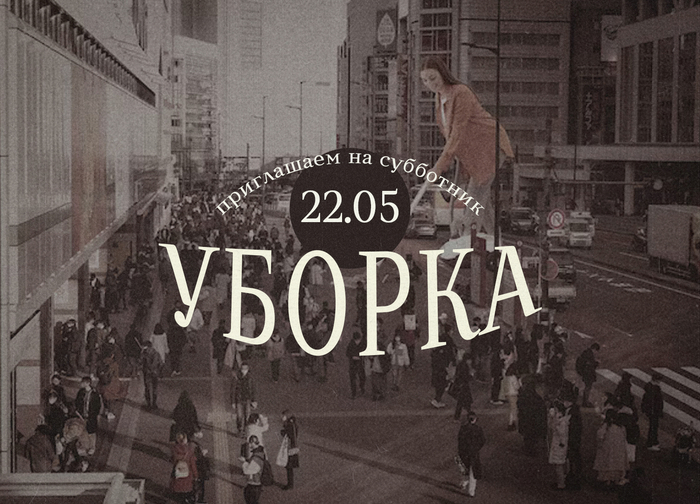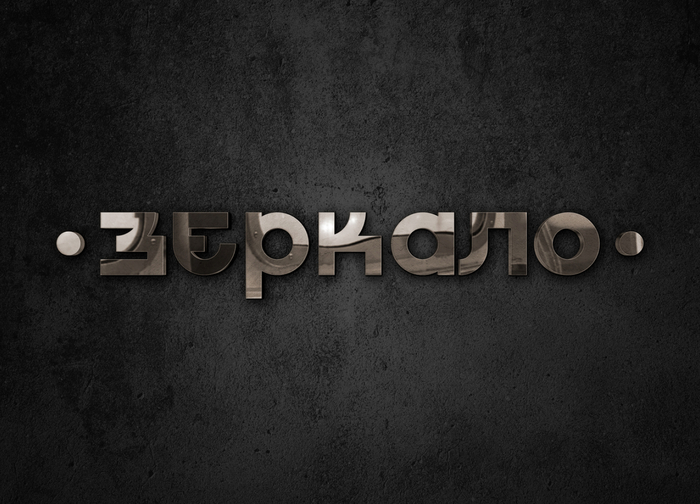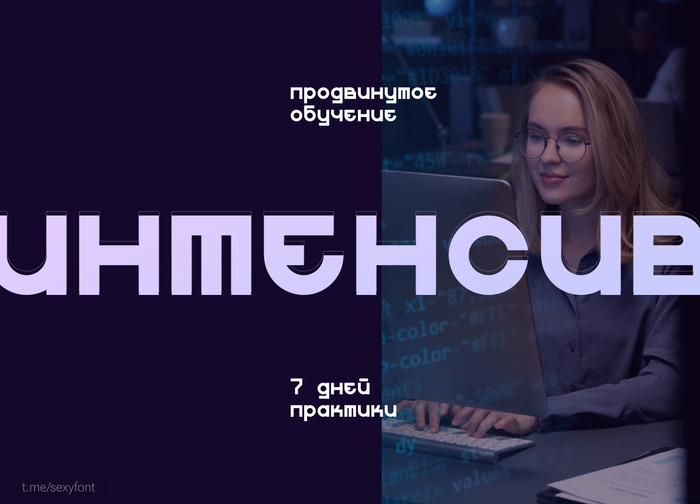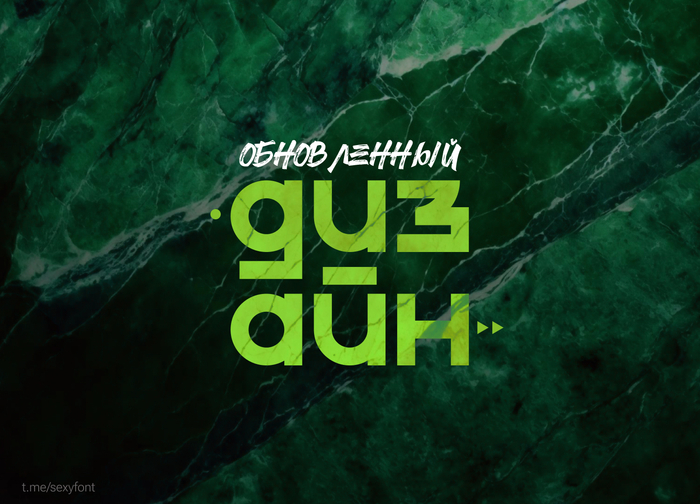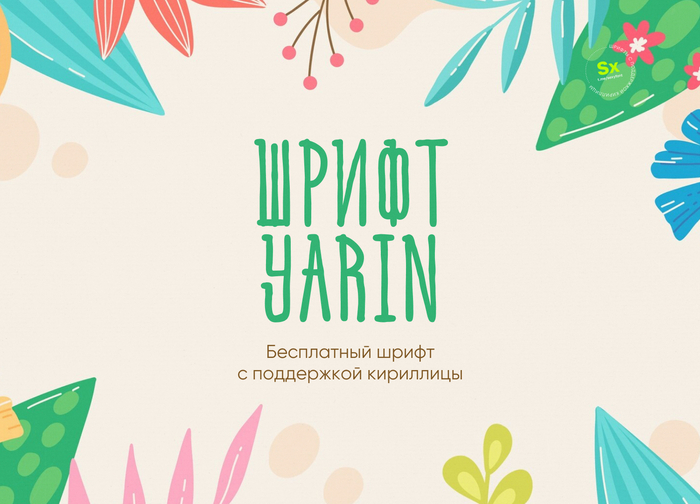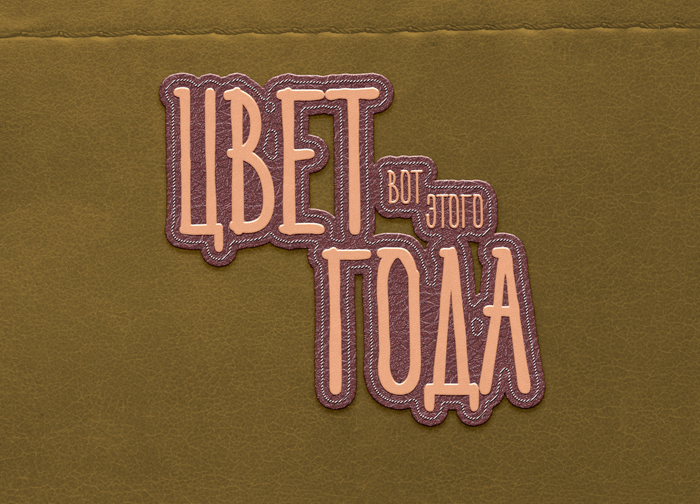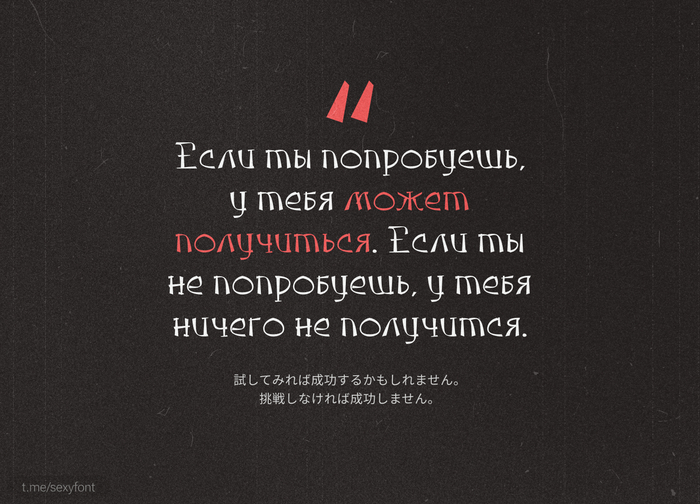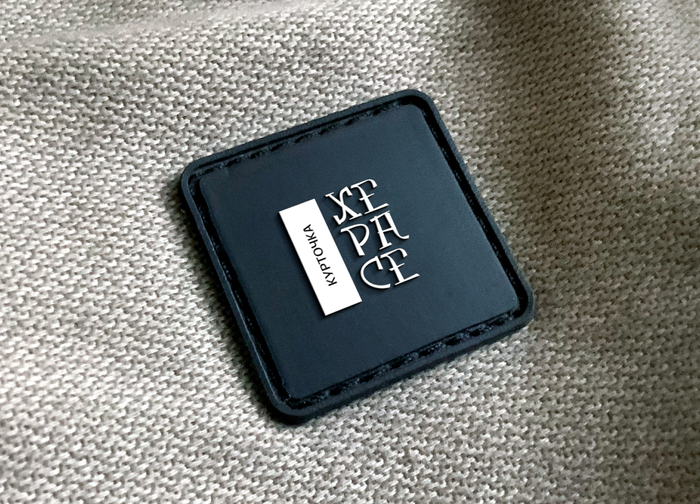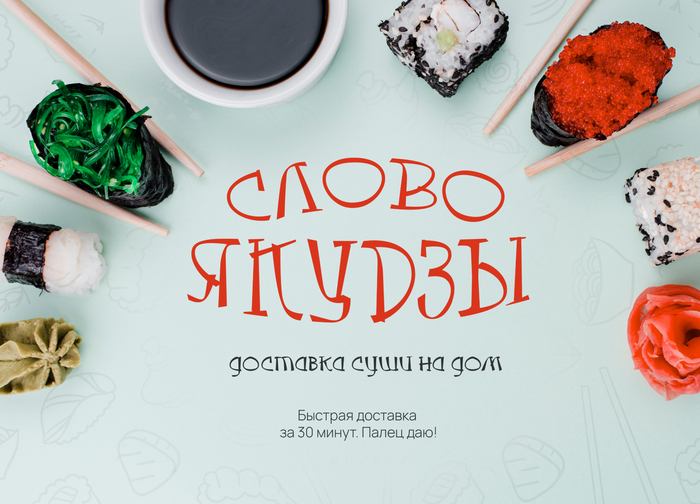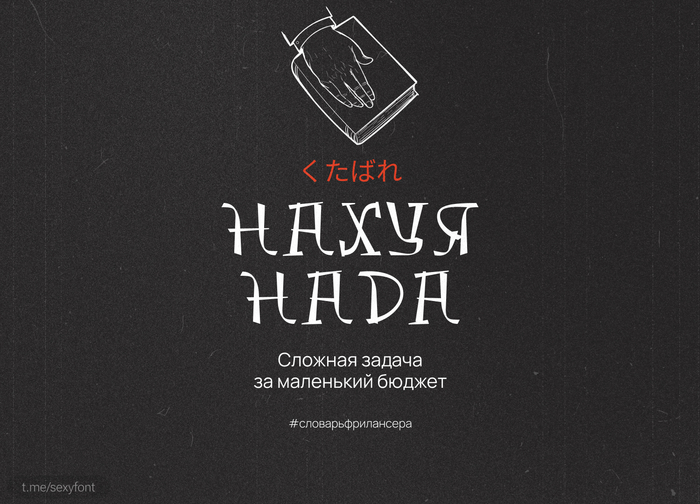
Шрифт в восточном стиле. Takashimura
Был вдохновлен уникальной японской каллиграфией и основан на японской концепции дизайна. Идеально подходит для создания творческих работ с японскими, азиатскими и восточными концепциями.
Шрифт Metrika. Бесплатная антиква
«Этот шрифт я сделал, как итоговый проект на курсе. С тех пор ничего в нём не менял. И только сейчас решил поделиться. Со всеми наивными ошибками и недоделками. Пусть будет! Итак, встречайте, Метрика!»
Шрифт practice
Шрифт practice. Бесплатный кириллический шрифт с острыми углами)
Шрифт Yarin
Чуть-чуть лета. Шрифт Yarin - это бесплатный шрифт, разработанный Марио Панделиевым и вдохновленный летней свободой.
Бесплатный шрифт из "ну погоди"
Ну заяц погодииии!! Шрифт wellwaitfree. Бесплатный игривый шрифт в стилистике оформления советского мультфильма "ну погоди" создан шрифтовым дизайнером из Сибири.
Шрифт Sagrada. Кириллица
Шрифт, вдохновленный готической архитектурой и кириллическими надписями. В каждом письме каждый может найти необычный мистический образ или персонаж.
Шрифт Матрёшка. Кириллица
Матрёшка. Веселый, почеркушный шрифт для твоих проектов. По лицензии в продаже не нашёл) Пока предположу, что бесплатный. Но это не точно.
Новая презентация. Шрифт Inglobal
Бесплатный кириллический шрифт) Не супер выразительный. Но вполне читабельный